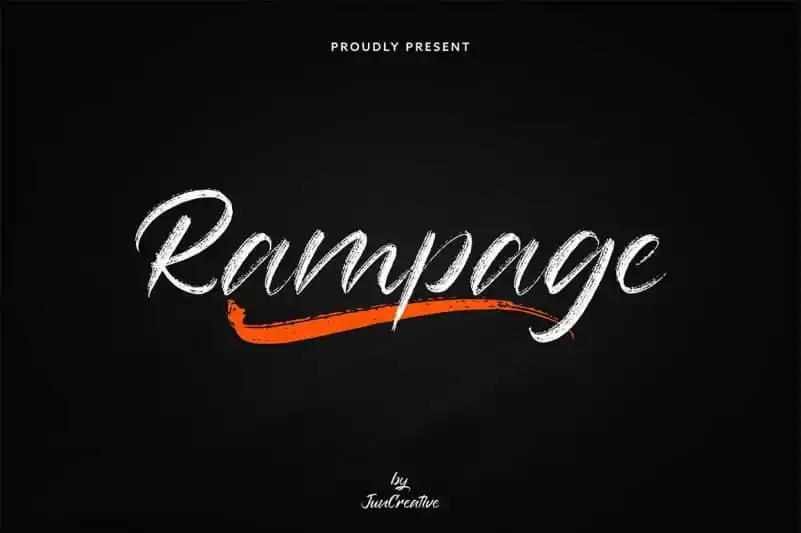
Rampage Brush Font – Download Grátis
A fonte Rampage Brush é uma escolha perfeita para designers que desejam adicionar um toque sofisticado e elegante aos seus projetos. Criada com a aplicação de pincel mais precisa, esta fonte é um design brilhantemente versátil, ideal tanto para títulos quanto para textos menores. Desenhada pela JunCreative, a Rampage Brush combina uma beleza natural e cuidadosamente elaborada, oferecendo uma abordagem contemporânea ao design que se adapta perfeitamente para diversas necessidades gráficas. Estendendo-se desde cinto de saída até cartazes, esta fonte é ideal para criar design no título, como roupas, convites, títulos de livros, desenhos de papelaria, citações, marcas, logotipos, cartões de agradecimento e embalagens. Seja em uma impressão de alta qualidade ou num design minimalista, a Rampage Brush oferece uma textura única que torna os seus projetos ainda mais interessantes e memoráveis.